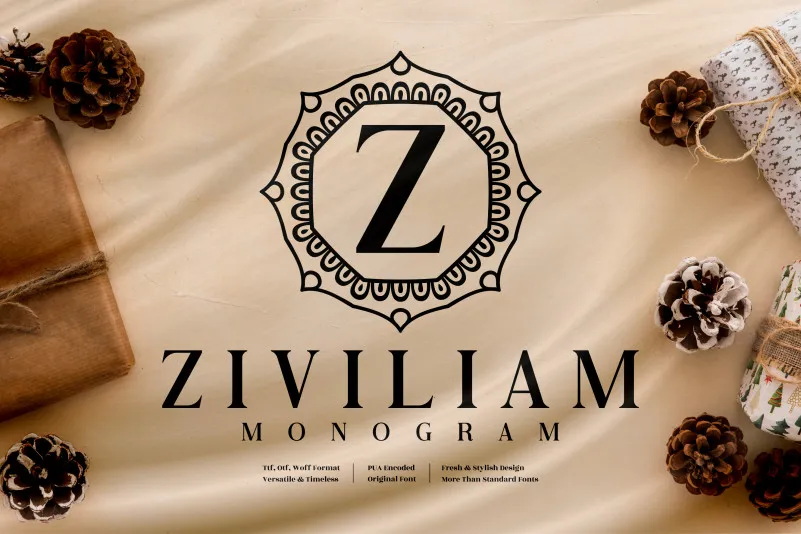
Ziviliam Monogram Font – Download Grátis
A Ziviliam Monogram Font é uma elegante fonte decorativa que destaca-se por seus ornamentos de folha luxuosos. Esta fonte não só oferece um toque sofisticado a qualquer projeto visual, mas também cria um ar intimista e encantador ideal para se tornar o coração da sua identidade visual. Seja você criando cartões de visita com estilo e sofisticação para seu trabalho, personalizando suas postagens nas redes sociais ou projetando um logo que transmita a natureza autêntica, esse design pode ser perfeitamente adaptado para qualquer aplicação onde desejará criar uma impressão de luxo e elegância. Além disso, esta fonte também se destaca como uma ótima opção para criações gráficas personalizadas, como cartões de aniversário criativos ou designs únicos de estátuas de papel. Com a Ziviliam Monogram Font da perspectype, você pode dar um toque de excentricidade e luxo a qualquer projeto visual que esteja planejando.